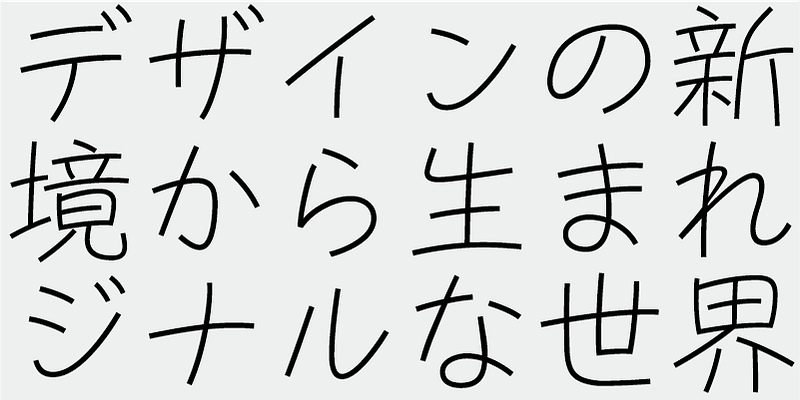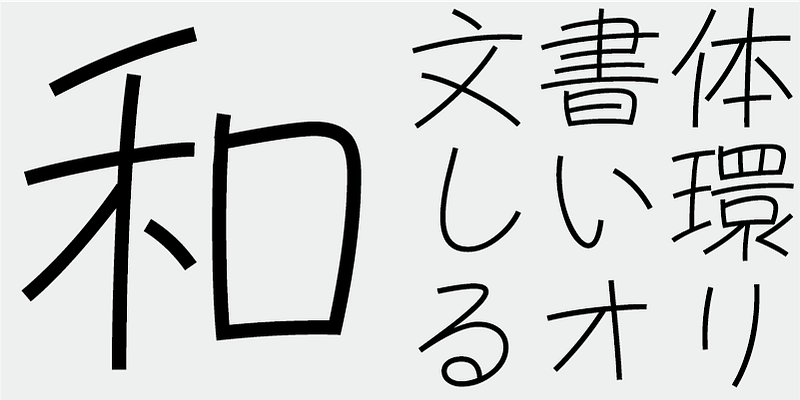
Con este tipo de letra es posible comunicar los sentimientos con un estilo de carácter manuscrito. Este tipo de letra recibe el nombre de “Circle“ ya que se utilizan muchos arcos para los glifos.
Este tipo de letra incluye los mejores 1.000 caracteres kanji elegidos a partir de tablas de frecuencia de caracteres elaboradas por empresas periodísticas, editoriales e institutos de investigación lingüística, además de 206 caracteres kana y signos de puntuación.
En la producción de fuentes japonesas de hoy en día, los 7000 caracteres del estándar JIS se consideran esenciales. Pero, ¿todas las fuentes realmente necesitan 7000 caracteres? En la época de la fotocomposición, se necesitaban muchos menos caracteres. FONT1000, un grupo de diseñadores de tipos de letra independientes, comenzó con esa sencilla pregunta. Hemos seleccionado el mínimo de 1000 caracteres kanji (ideográficos) necesarios para la composición tipográfica en japonés y nos hemos esforzado en crear tipos de letra y fuentes de forma activa para admitirlos. Este conjunto de 1000 caracteres kanji se seleccionó utilizando datos de frecuencia de caracteres recopilados por empresas de periódicos, editoriales, organizaciones de investigación lingüística, etc., y también incluye caracteres silábicos kana y signos de puntuación. FONT1000 se formó en 2001 con 25 diseñadores y 25 tipos de letra. Hoy tenemos 130 tipos de letra y hemos crecido hasta incluir casi 40 miembros, lo que hace posible trabajar con tipos de letra con más caracteres.